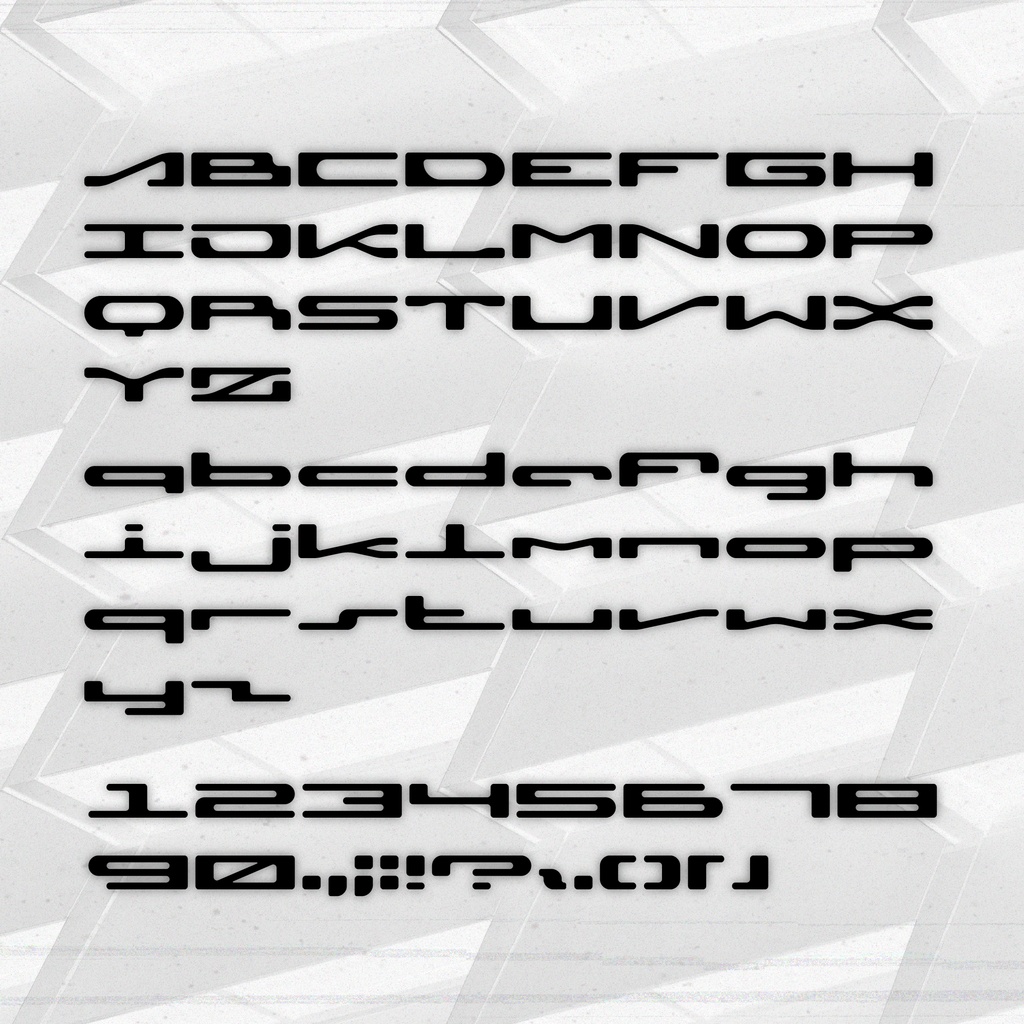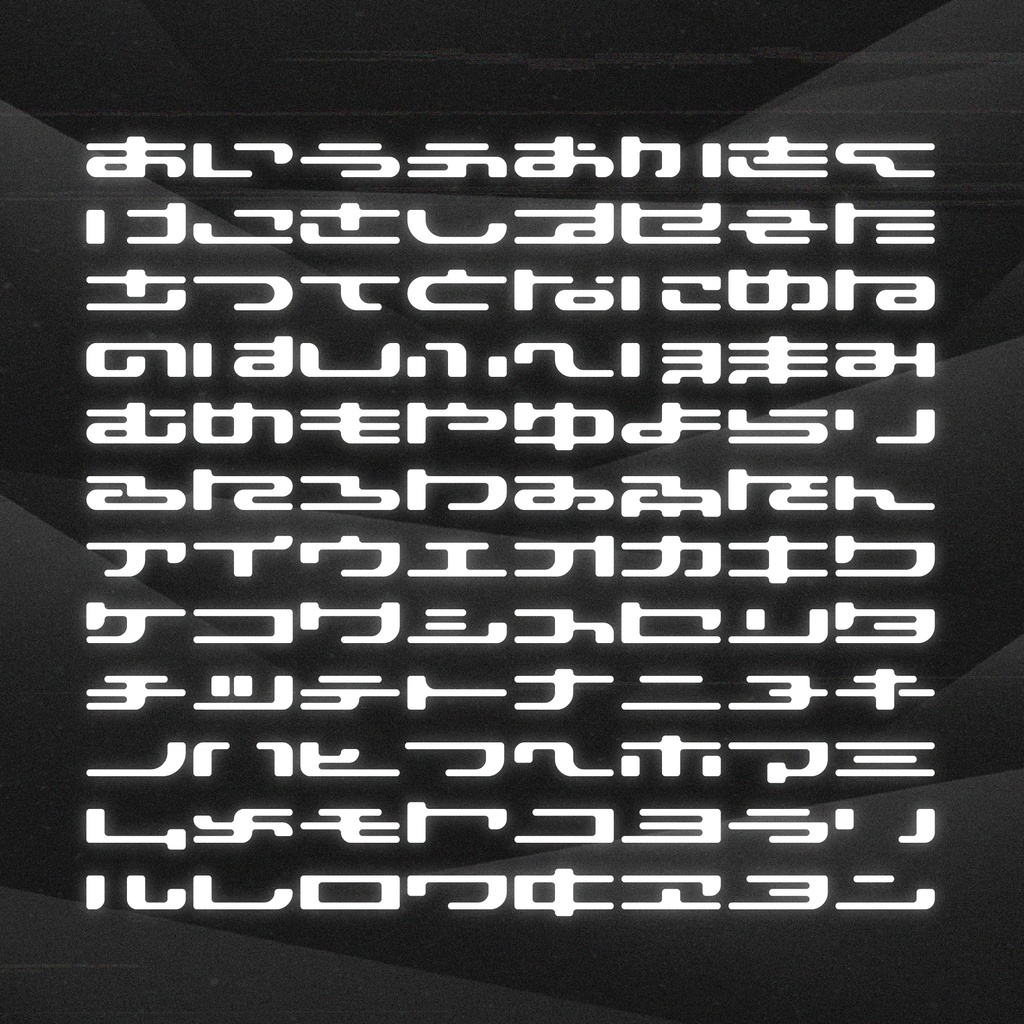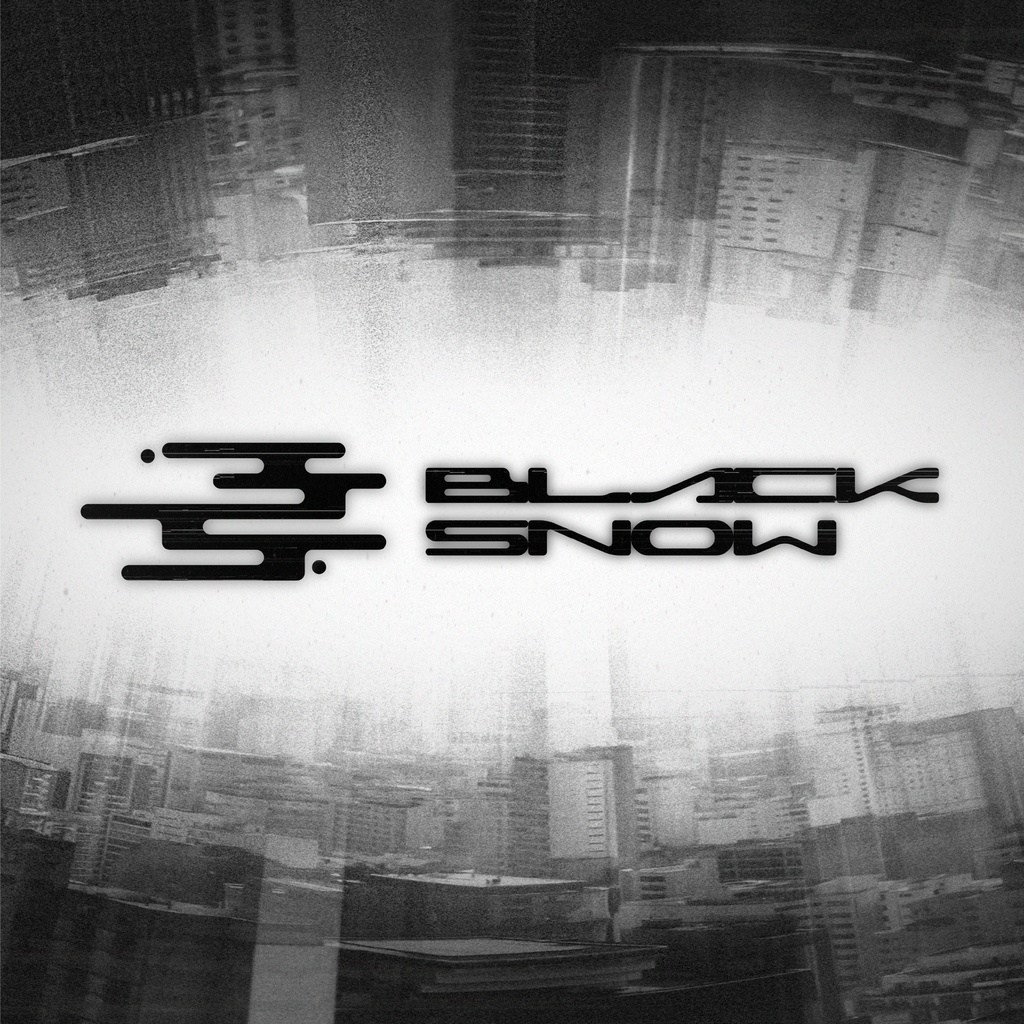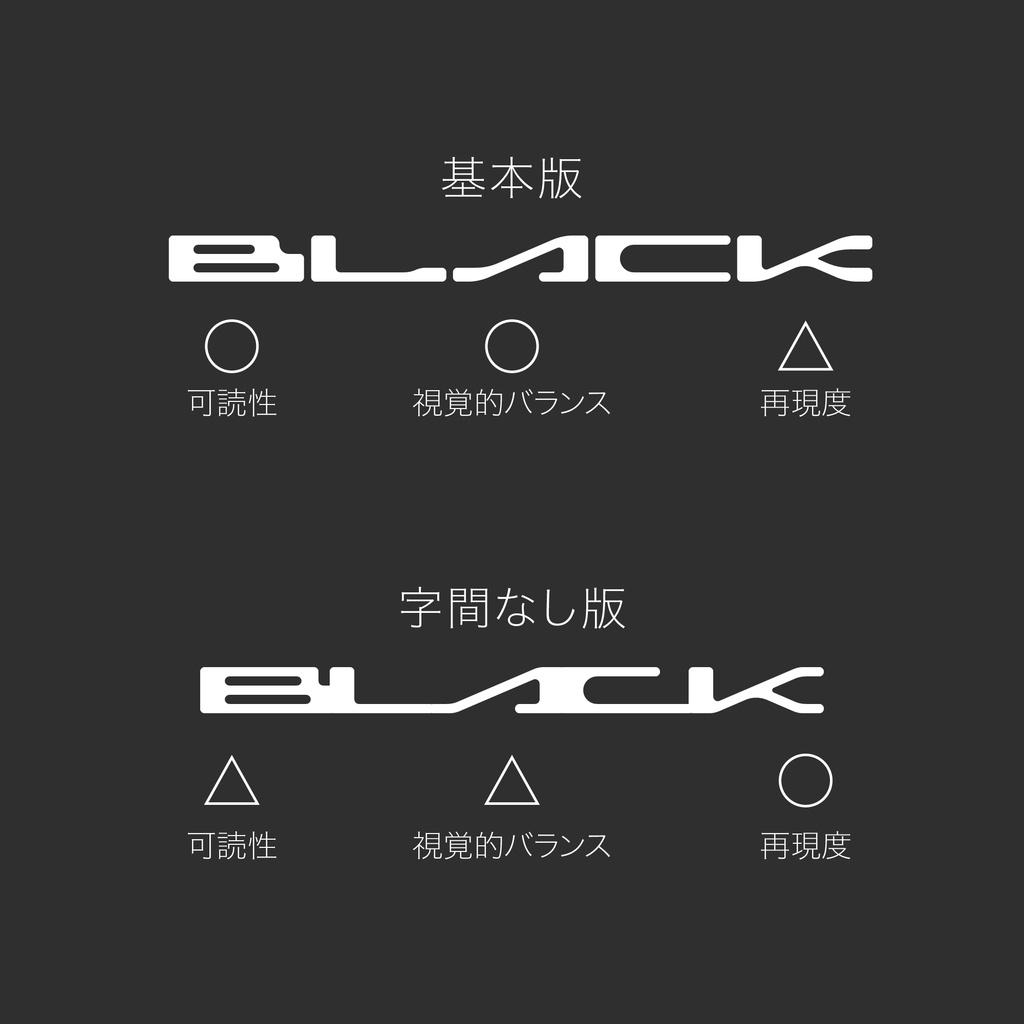
🔳 BLACK SNOW / 黑雪 🔳 📢📢📢📢📢📢📢📢📢 特記事項 📢📢📢📢📢📢📢📢📢 リツイートで新フォントを配布する企画を開催中。 📢新しいフォントが掲示ツイートが目標達成から1ヶ月間のみ無料配布され、その後は有料となりますが。また、配布開始ツイートが毎回100RTの倍数を超えると、まだ1ヶ月間無料でDLできます。📢 ✨✨✨今回のフォントは、他のロゴからインスピレーションを得て、同じようなスタイルのフォントを制作できるかどうかに挑戦しています。 選んだロゴの特徴は、すべての文字が繋がっていて、文字の角丸だけが主要な識別方法です。 したがって、今回のデザインは、元のデザインの特徴を再現し、使用可能なフォントを最終目標としています。 元のデザインの特徴を再現するために、フォントの汎用性が低下する可能性があるため、今回は基本版と字間なし版の2つバージョンを配布する予定です。✨✨✨ 今回のデザインの制作過程はここで: https://twitter.com/amari_design/status/1631567691264970755?s=20 ☕️価格設定には、デザインへの集中力を維持するために、缶コーヒーに大きく依存しているです。 そのため、大体の制作日数×日本での缶コーヒーの値段でフォントの価格を算出することにします。☕️ 📢📢📢📢📢📢📢📢📢 デザイン説明 📢📢📢📢📢📢📢📢📢 同じ構成で英語と全仮名を含むの挑戦をするために作られたフォント。 一切考えず、統一された構成の可能性を探る、表現力だけを追求した極太字フォントです。 📢📢📢📢📢📢📢📢📢 利用規約 📢📢📢📢📢📢📢📢📢 個人、商用どちらでも利用可能です。 ✨フォントが使用されたら、ツイッターにお知らせくださいhttps://twitter.com/amari_design✨ 本素材を使用した作品については、リツイートなどの形で宣伝させていただく場合があります。 フォントのインストール等の技術的なサポートはいたしません。使用して発生したと思われる如何なる問題についても、作者は責任を負わないものとします。 著作権を放棄することはありません。 商標を登録したり、作者であると主張したり、データ自体を販売または再販したりすることは禁じられています。 このコンテンツの最終的な解釈権は作者に帰属します。 内容補充とバージョン更新は製作続けるです。使用する際は最新バージョンにご注意ください。 📢📢📢📢📢📢📢📢📢 収録內容 📢📢📢📢📢📢📢📢📢 ラテン文字、数字、仮名だけてを含む290通常/350字間なしグリフが含まれています。 ーーーーーーーーーーーー Twitter:https://twitter.com/amari_design Behance:https://www.behance.net/9f45706b ーーーーーーーーーーーー